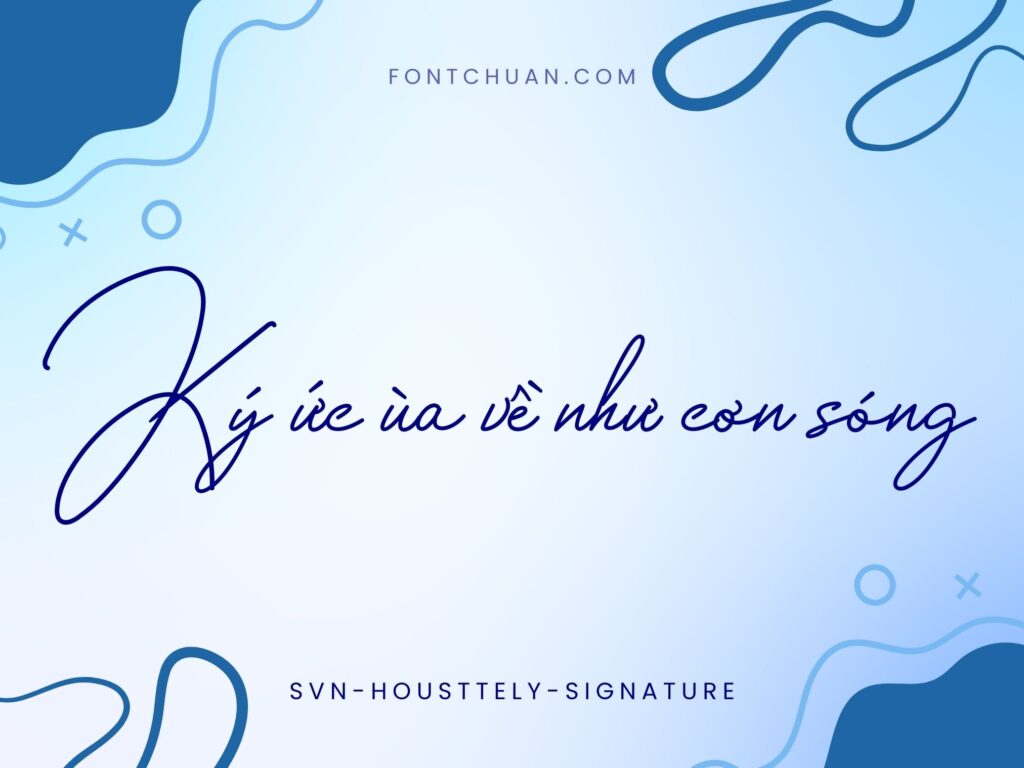
Font SVN Housttely Signature Việt Hóa
Font SVN Housttely Signature là phiên bản Việt hóa của kiểu chữ Housttely Signature, được thực hiện bởi STYLEno.1 Fonts. Đây là một Font chữ viết tay theo phong cách monoline, mang lại sự tự nhiên, hiện đại và thanh lịch trong từng nét chữ. Nhờ vào thiết kế mềm mại, Housttely Signature cũng gợi liên tưởng đến sự uyển chuyển của Font chữ thư pháp, nhưng được giản lược để phù hợp hơn với các dự án thiết kế mang tính ứng dụng cao. Font này bao gồm các ký tự chữ hoa, chữ thường, chữ số và dấu câu, hỗ trợ đa ngôn ngữ. Với phong cách tinh tế, Housttely Signature phù hợp cho nhiều mục đích sử dụng như thiết kế logo, thương hiệu, thiệp mời, bài đăng trên mạng xã hội, quảng cáo, bao bì sản phẩm, nhãn mác, nhiếp ảnh, watermark và các dự án yêu cầu phong cách chữ ký.
SVN Housttely Signature lý tưởng cho các dự án thiết kế yêu cầu sự thanh lịch và chuyên nghiệp, như thiết kế logo thương hiệu, thiệp mời đám cưới, tiêu đề tạp chí và các ấn phẩm truyền thông. Các ngành nghề như thiệp cưới, giáo dục và quảng cáo có thể tận dụng font này để tạo điểm nhấn trong thiết kế. Ngoài ra, font cũng thích hợp cho các sự kiện như Valentine, Sinh nhật, Tết và các lễ hội khác.